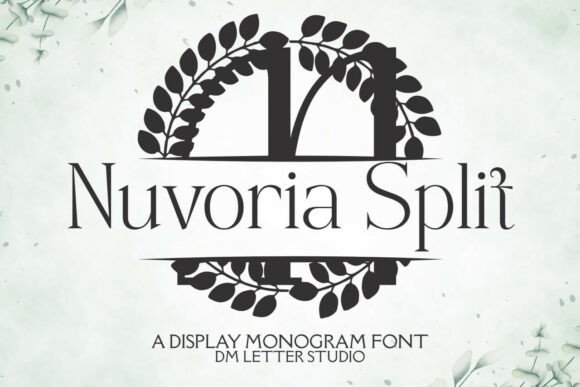
Nuvoria Split Monogram
Nuvoria Split Monogram์™€ ๊ฐ™์€ ๊ณ ํ’ˆ์งˆ ์ž์‚ฐ์„ ์ฐพ๊ณ  ์žˆ๋‹ค๋ฉด ์ด ํ”„๋ฆฌ๋ฏธ์—„ ํŒจํ‚ค์ง€๋Š” ์ฐฝ์˜์ ์ธ ํ”„๋กœ์ ํŠธ๋ฅผ ์œ„ํ•œ ํ™˜์ƒ์ ์ธ ์„ ํƒ์ž…๋‹ˆ๋‹ค.
POD(์ฃผ๋ฌธํ˜• ์ธ์‡„) ์ œํ’ˆ, ๊ฒฐํ˜ผ์‹ ์ดˆ๋Œ€์žฅ ๋˜๋Š” ์†Œ์…œ ๋ฏธ๋””์–ด ๊ทธ๋ž˜ํ”ฝ์„ ๋งŒ๋“ค ๋•Œ Nuvoria Split Monogram๋Š” ์ด์ƒ์ ์ธ ์„ ํƒ์ž…๋‹ˆ๋‹ค.